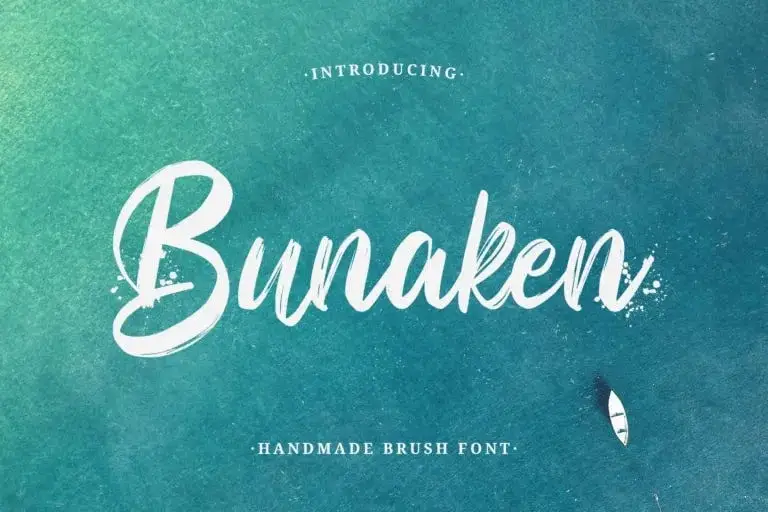
Bunaken Brush Font – Download Grátis
Bunaken Brush Font é mais do que uma simples tipografia escrita a mão com traços suaves. Este design se tornou um refleto real do espírito contemporâneo e elegância. Foi criado pelo typefactory e compartilhado no ambiente de criação online 99designs, garantindo-o como uma opção indispensável para designers digitais. Seu estilo robusto e sofisticado, combinado com caracteres grossos e estendidos que são adequados em tudo do logotipo à embalagem. É perfeitamente adaptado para uso em logos, criação de marca e design de embalagens. Este design de script rústico é um verdadeiro mimo, oferecendo-lhe uma ferramenta poderosa para suas projetos digitais atuais e futuros.